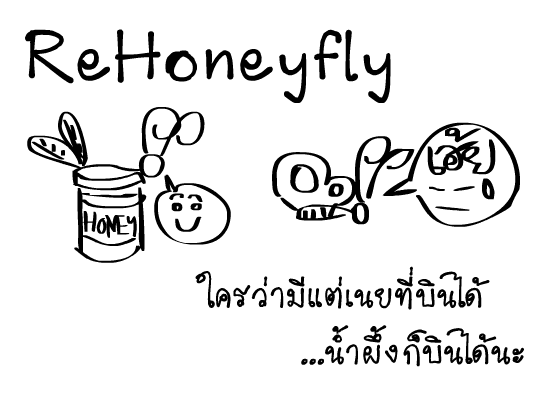
ทำฟ๐นต์ใหม่ค่ะ
หลังจากตายไปนาน
มาขยันแบบขี้เกียจสักหน่อย
(ก็อย่างที่เห็นแหละครับ ไม่ต้องอธิบายมากว่าขยันแบบขี้เกียจคืออะไร  :08:)
เร่มาตั้งจู๋ แถมพูดค่ะด้วย  :25:
ดูเป็นลายมือผู้หญิงดีจัง น่ารักดีค่ะ  :33:
เอ่อ เพิ่งจะเก็ท.. butterfly